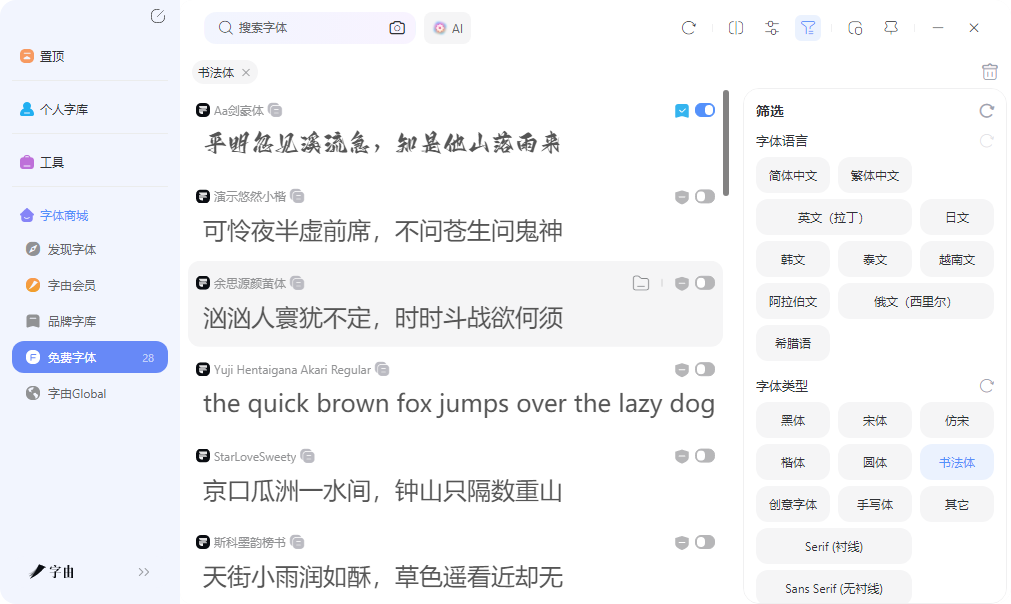
毛笔字在线生成器,几个工具直接解决你的毛笔字体需求
做茶叶包装、餐厅招牌、国潮海报,毛笔字能让整个设计的气质提上来。但大部分设计师不会写毛笔字,电脑默认字体里也没有像样的毛笔字体。去网上下载毛笔字体,装完发现缺字、效果差、版权不明。现在有很多在线毛笔字生成器,输入文字就能生成毛笔字效果,有的还能下载矢量文件,可以直接用于印刷。本文实测了5款毛笔字相关工具,从单字查询到多字作品生成,从在线预览到商用授权,可以根据自己的需求来选择。
首先我推荐的是字由,字由平台提供两种生成毛笔字的方式:AI字体一键生成毛笔字图片,以及字体库中激活毛笔字体后在设计软件中使用。
字由AI字体功能内置了国潮风、手写书法等分类模板。这些模板中的一部分是毛笔书法风格,包括行书、楷书、草书等。用户打开字由客户端,进入AI工具下的AI字体页面,在左侧标签栏选择国潮风或手写书法分类,系统会展示该分类下的所有模板。
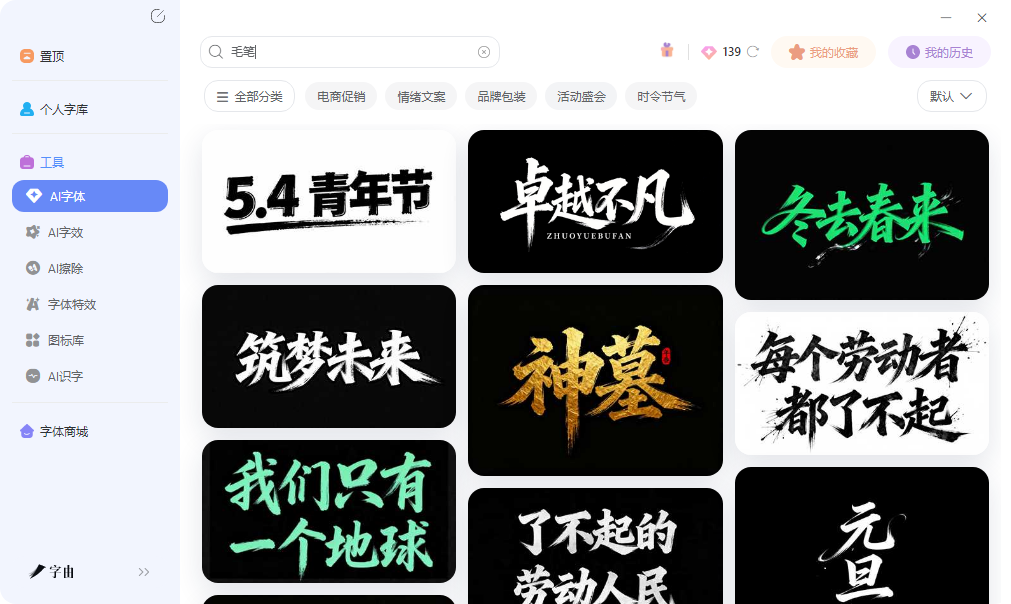
每个模板的字体、特效、排版和背景参数都已预设好。用户输入自己的文案,选择一个模板,点击生成按钮,系统输出透明背景的PNG图片。生成一张图片消耗3个算力点,每日登录赠送6个点。这个功能适合需要快速出一张毛笔字标题图的场景,例如电商大促海报、活动封面。
字由字体库中收录了多款毛笔书法字体,包括点字文人榜书、点字禄军行楷、汉仪苏泽立行楷精修版、演示悠然小楷等。用户在字由客户端搜索毛笔或行楷等关键词,找到需要的字体,点击激活按钮。激活后,该字体出现在PS、AI、Word的字体列表中。
用户在设计软件中输入文字,选择该字体,即可自由排版、调节字号和颜色。这种方式适合需要长期、反复使用同一款毛笔字体的项目,例如品牌VI、系列包装、书籍封面。激活的字体支持云字库同步,换电脑登录同一账号即可使用,无需重新安装。字由平台的毛笔字体部分标注免费商用,部分需要会员或单独授权,使用前查看字体详情页的授权标签即可。
2、书法迷
第二个网站是书法迷。它是一个综合性的书法资源平台,提供五体书法字典、书法字体下载、书法印章等功能。其核心功能是五体书法字典:用户可以输入单个汉字,查询该汉字在草书、行书、楷书、隶书、篆书五种书体中的名家写法。每个书体下会展示多个书法家的写法示例。书法迷适合书法学习者和设计师查询某个特定汉字的传统毛笔写法,作为设计参考或灵感来源。它不直接生成整段文字的毛笔字图片,而是提供历代书法家的单字写法集合。用户可以将查询结果截图使用,或参考其笔画结构自行设计。该网站免费使用,无需注册。
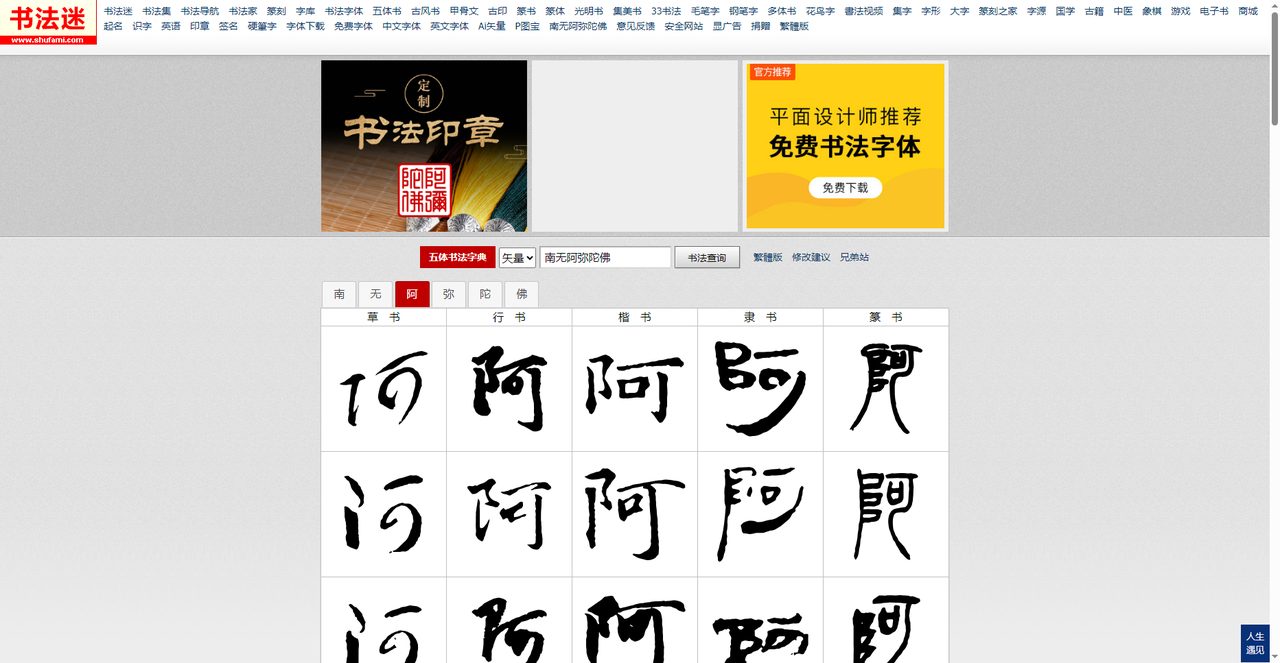
3、AI书法生成
第三个工具是AI书法生成。它支持输入多字内容,选择落款,系统生成完整的书法作品图片。页面介绍称:在线生成具有专业味道的书法作品,随机挑选数百种组合,支持下载图片或分享到朋友圈。同时也支持单个汉字和多个汉字查询,覆盖真草隶篆行五种书体。用户关注其微信公众号后,可以在微信中直接回复要生成的内容,系统返回书法作品。这个工具适合需要生成一句完整诗句、品牌slogan或对联等较长文本的用户,生成的作品可以作为设计参考或社交媒体配图。免费使用,生成结果可下载。
4、GoLogo
第四个网站是GoLogo。它专门用于在线生成毛笔字Logo。用户输入品牌名称,点击立即生成毛笔字,系统会输出多个毛笔字Logo方案。页面标注免费生成、可商用、矢量源文件。生成的Logo支持下载矢量格式(如SVG、EPS),放大不失真,适合用于招牌、包装、名片等印刷品。GoLogo也提供了行业分类筛选,用户可以选择餐饮、文化、科技等类别,系统会匹配更贴合行业属性的毛笔字风格。对于初创企业、个体商户、自媒体账号需要快速制作品牌标识的用户,GoLogo是一个低成本高效率的解决方案。免费版生成的Logo有水印或低分辨率,矢量文件下载可能需要付费或注册,具体以网站当前政策为准。
5、艺学网
第五个网站是艺学网的毛笔字体在线生成器。页面提供多种毛笔字体选项,例如斌纹锋行草、新蒂赵孟楷书、田氏颜真卿书法等。艺学网的优点是可以对比不同毛笔字体在同一段文字上的效果,同时支持简单的特效调节。如果你想要一个带倒影或渐变效果的毛笔字标题,可以在生成后直接下载。该工具适合个人使用,商用需注意字体授权,页面未明确标注可商用,建议咨询后使用。
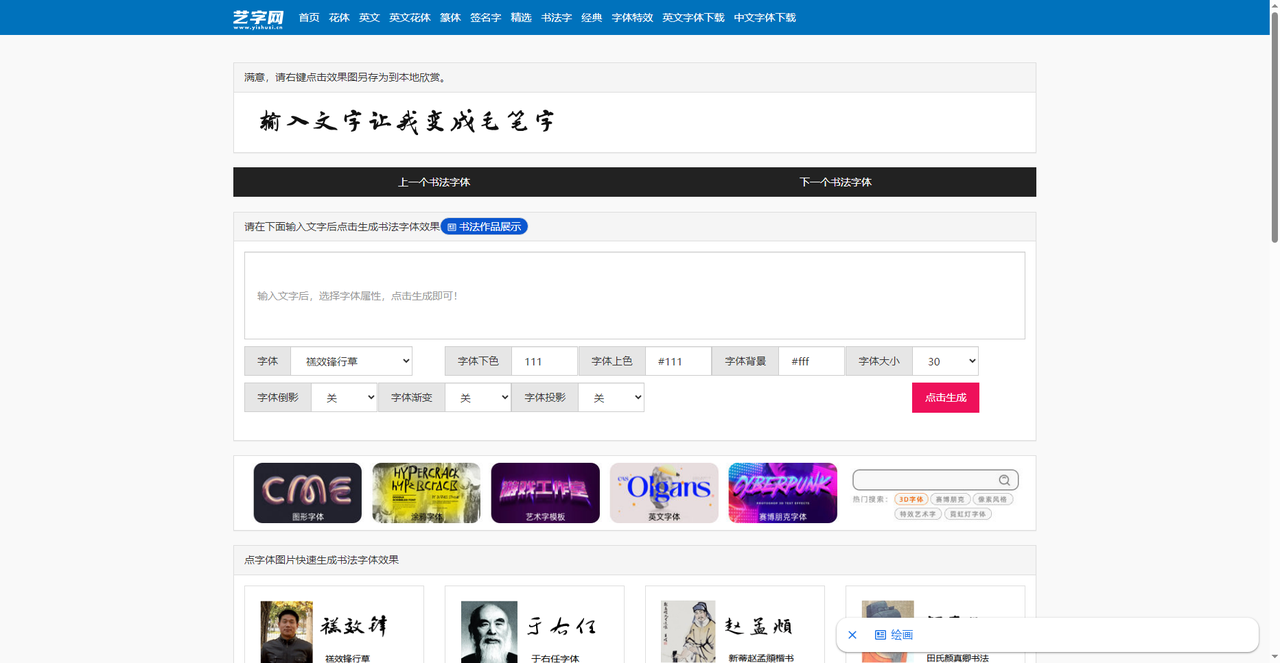
这其中我最推荐字由,字由提供AI图片生成和字体激活两种方式,适合设计师的日常使用,而且里面还有很多功能等你解锁,每一个都非常实用。其他的话,书法迷适合查询单个汉字的传统书法写法;AI书法生成(书法味)适合生成完整诗句或对联作品,支持落款;GoLogo专注于毛笔字Logo设计,支持矢量文件下载,可商用;艺学网提供多种毛笔字体在线转换,支持倒影、渐变等特效调节。输入文字,选择适合的毛笔字风格,几秒钟就能得到毛笔书法效果。